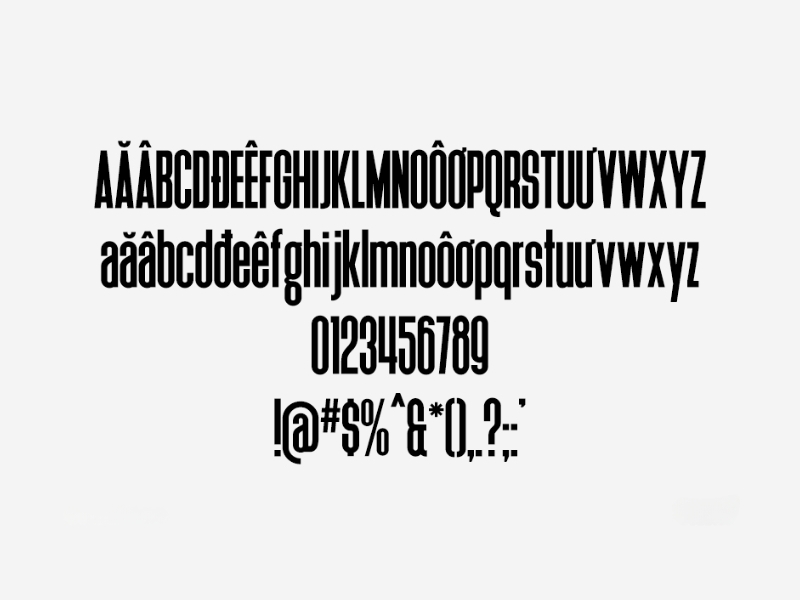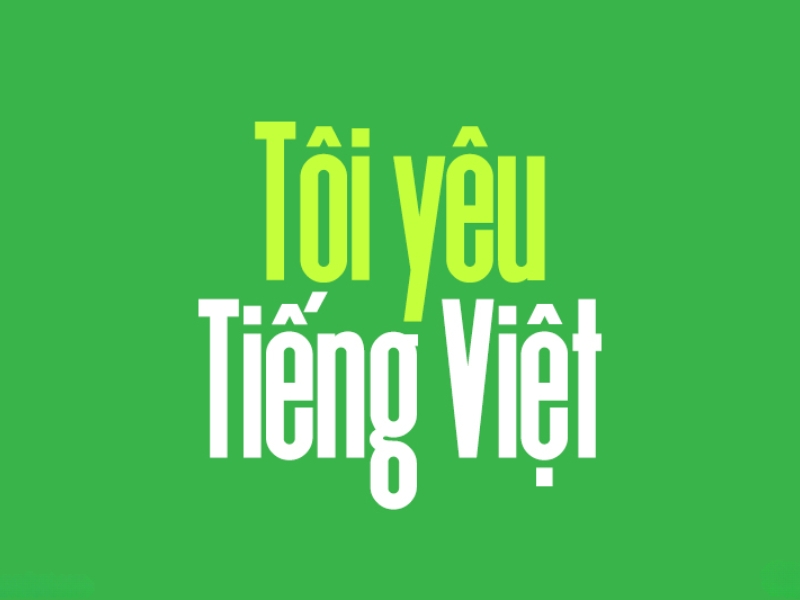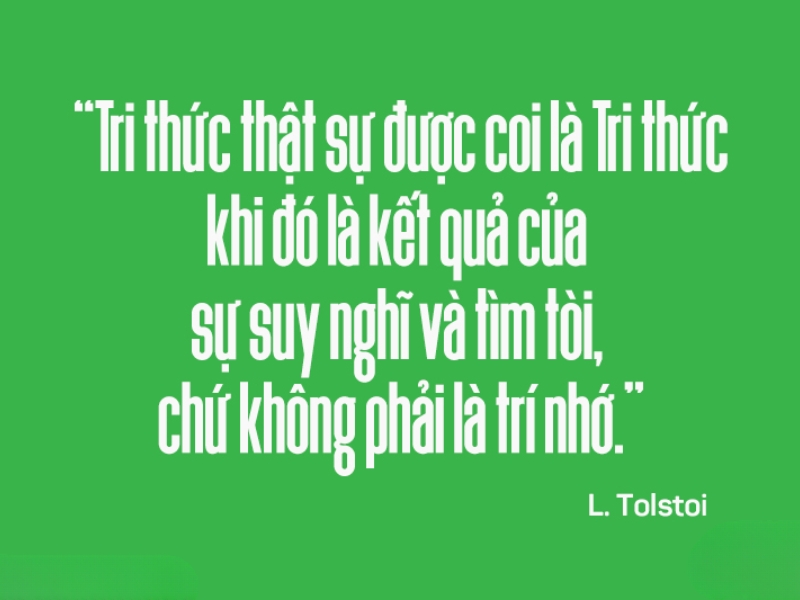
Font Việt hóa SVN Heathergreen là lựa chọn hoàn hảo cho những ai đang tìm kiếm một kiểu chữ viết tay nhẹ nhàng, tinh tế để ứng dụng trong thiết kế thiệp, logo hay ấn phẩm truyền thông. Với phong cách mềm mại, tự nhiên và giàu tính nghệ thuật, font này không chỉ giúp tăng tính thẩm mỹ mà còn tạo điểm nhấn ấn tượng cho mọi thiết kế.
Phông chữ SVN Heathergreen việt hóa là lựa chọn lý tưởng cho các thiết kế mang phong cách nhẹ nhàng, nghệ thuật như thiệp cưới, logo, poster hay bao bì quà tặng. Phiên bản việt hóa đã được tối ưu đầy đủ dấu tiếng Việt, giúp bạn sử dụng dễ dàng mà không gặp lỗi hiển thị khi thiết kế hoặc in ấn.
Đặc điểm nổi bật của font SVN Heathergreen Việt hóa
Font SVN Heathergreen Việt hóa được ưa chuộng nhờ sự kết hợp hài hòa giữa tính thẩm mỹ và khả năng ứng dụng linh hoạt trong thiết kế. Dưới đây là những đặc điểm nổi bật giúp font này trở thành lựa chọn lý tưởng cho nhiều dự án sáng tạo:
- Nét chữ mềm mại, tự nhiên: Font mang phong cách viết tay uyển chuyển, các đường nét liền mạch tạo cảm giác nhẹ nhàng, gần gũi và giàu tính nghệ thuật.
- Hỗ trợ đầy đủ ký tự tiếng Việt: Bộ font đã được Việt hóa chuẩn, hiển thị đầy đủ dấu tiếng Việt, hạn chế lỗi font khi sử dụng trong thiết kế và in ấn.
- Tính thẩm mỹ cao: Kiểu chữ thanh thoát, tinh tế, phù hợp với các thiết kế cần sự sang trọng và cảm xúc như thiệp cưới, logo hoặc bao bì cao cấp.
- Dễ dàng kết hợp trong thiết kế: Có thể phối hợp linh hoạt với các font sans-serif hoặc serif để tạo bố cục cân đối, giúp tổng thể thiết kế hài hòa và chuyên nghiệp hơn.
Ứng dụng của font Việt hóa SVN Heathergreen
Phông chữ SVN Heathergreen Việt hóa được sử dụng rộng rãi trong nhiều lĩnh vực thiết kế:
- Thiết kế thiệp cưới, thiệp mời, card chúc mừng
- Làm logo thương hiệu cá nhân, shop thời trang, mỹ phẩm
- Thiết kế poster, banner quảng cáo
- Trang trí bao bì quà tặng, sản phẩm handmade
- Sử dụng trong content mạng xã hội (Instagram, Pinterest…)
5 lưu ý khi sử dụng font SVN Heathergreen Việt hóa
Để đảm bảo tính thẩm mỹ và hiệu quả khi ứng dụng font Việt hóa SVN Heathergreen trong thiết kế, bạn nên lưu ý một số điểm quan trọng sau:
- Sử dụng đúng mục đích: Đây là font viết tay mang tính trang trí cao, phù hợp cho tiêu đề, slogan hoặc điểm nhấn. Không nên dùng cho đoạn văn dài vì sẽ gây khó đọc.
- Kết hợp font hợp lý: Nên phối cùng các font đơn giản như sans-serif hoặc serif để tạo sự cân bằng, giúp bố cục rõ ràng và chuyên nghiệp hơn.
Tuân thủ những lưu ý trên sẽ giúp bạn khai thác tối đa vẻ đẹp của font SVN Heathergreen, đồng thời đảm bảo thiết kế luôn chuyên nghiệp và đồng bộ.